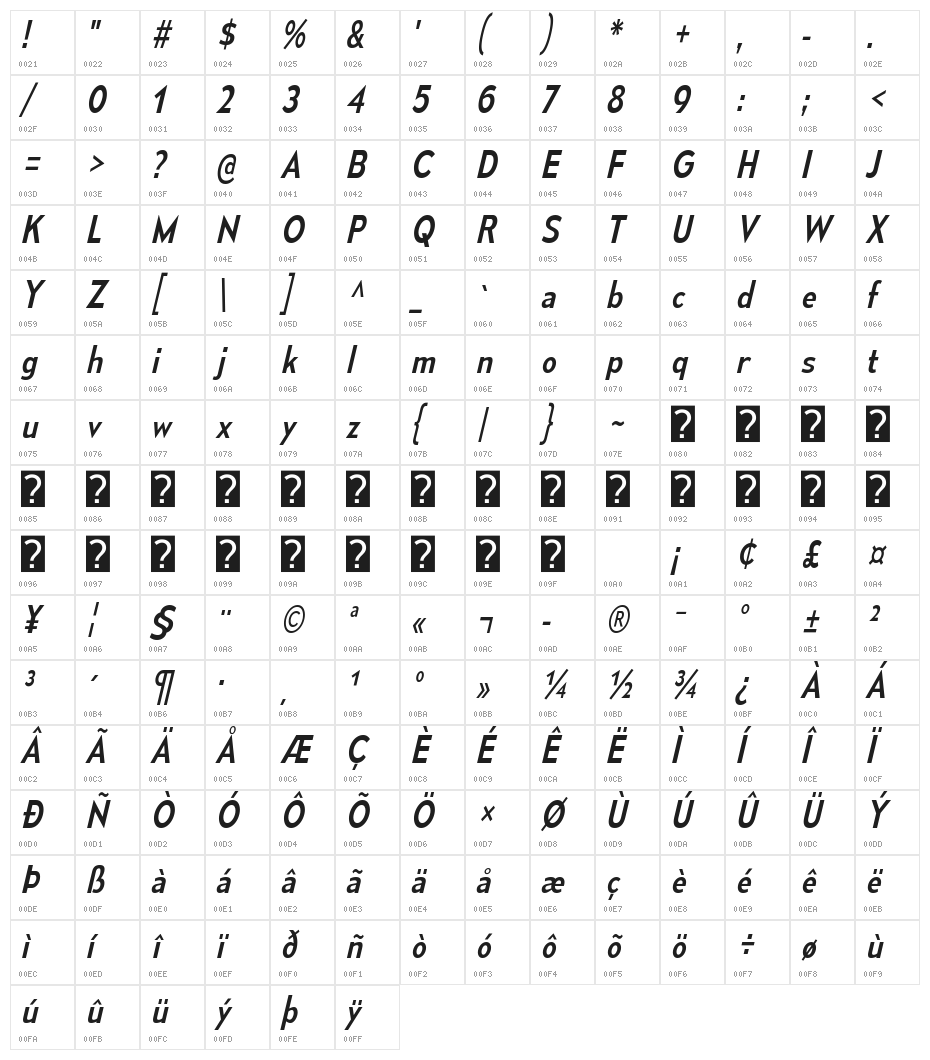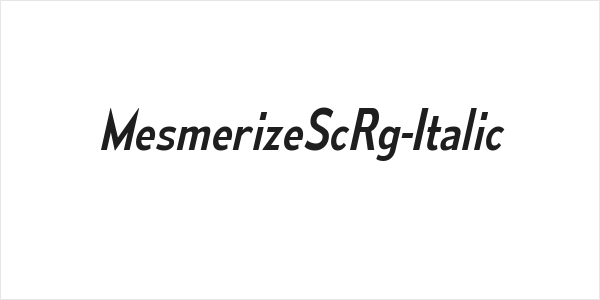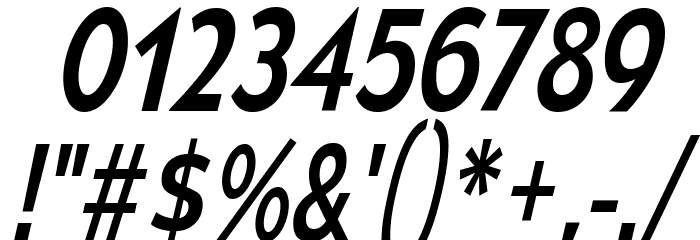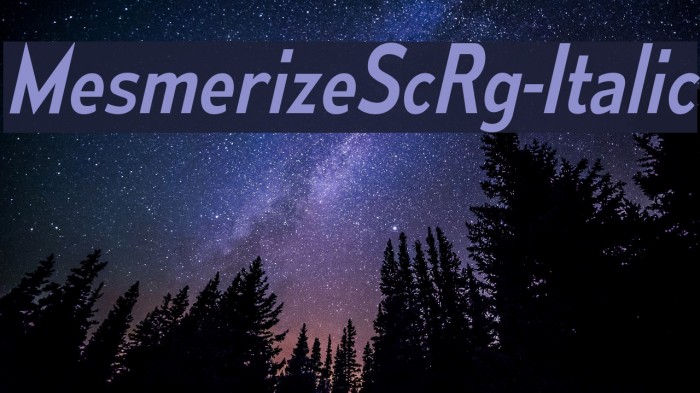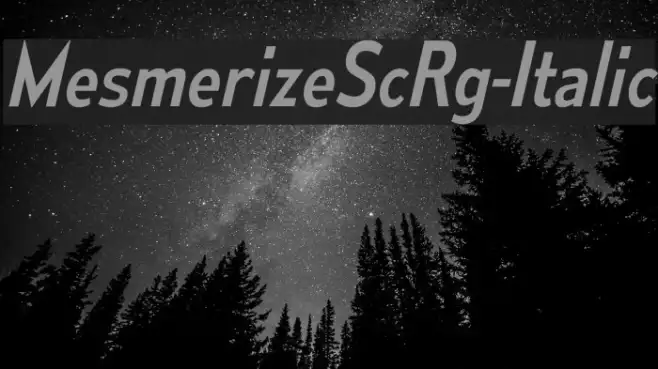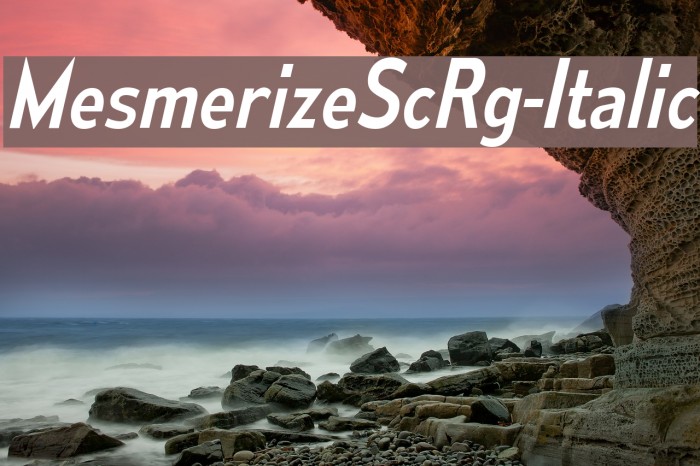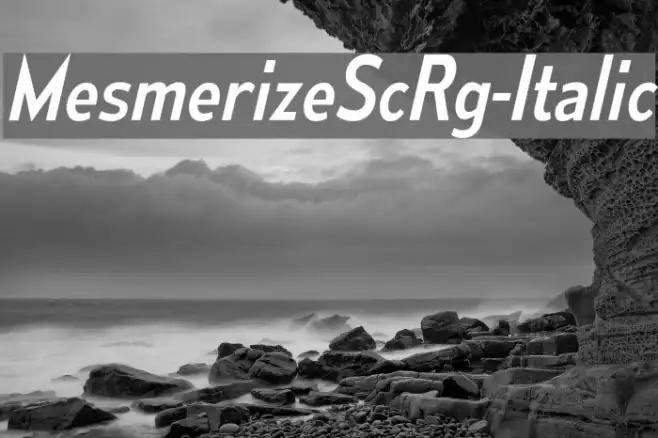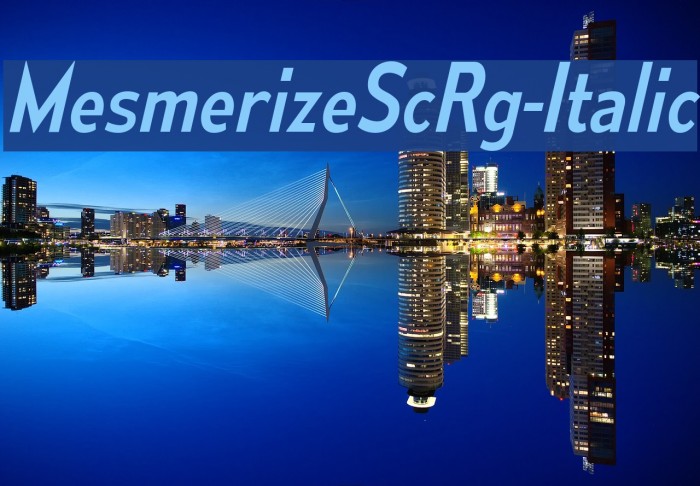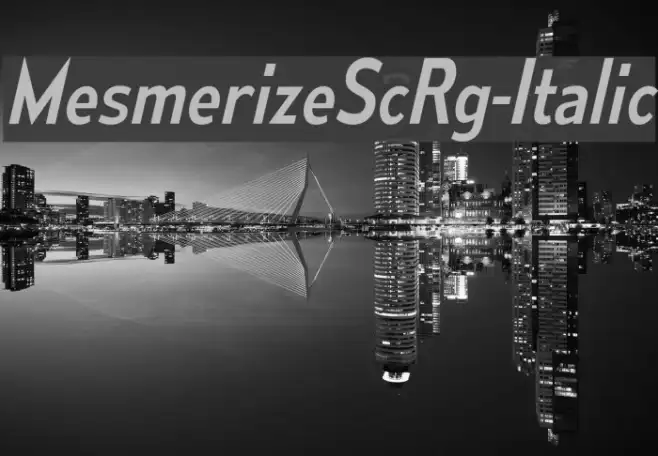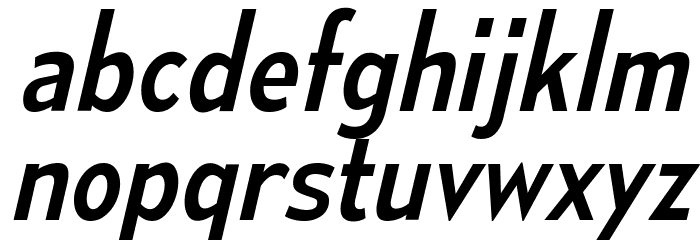
MesmerizeScRg-Italic Font
| Caso de uso | Headlines, Body text, Logos |
| Proyectos propuestos | Ideal for branding, advertising, and editorial design projects that require a modern and sophisticated touch. |